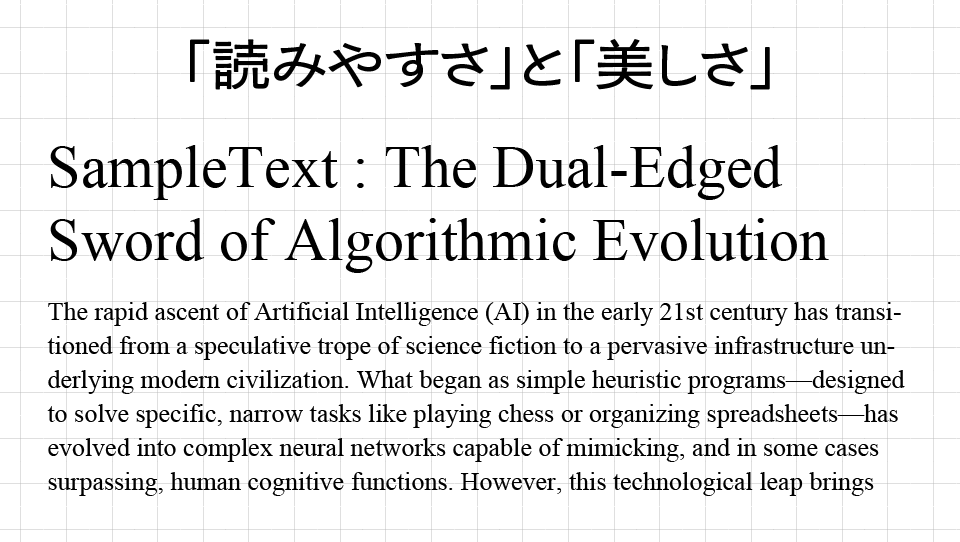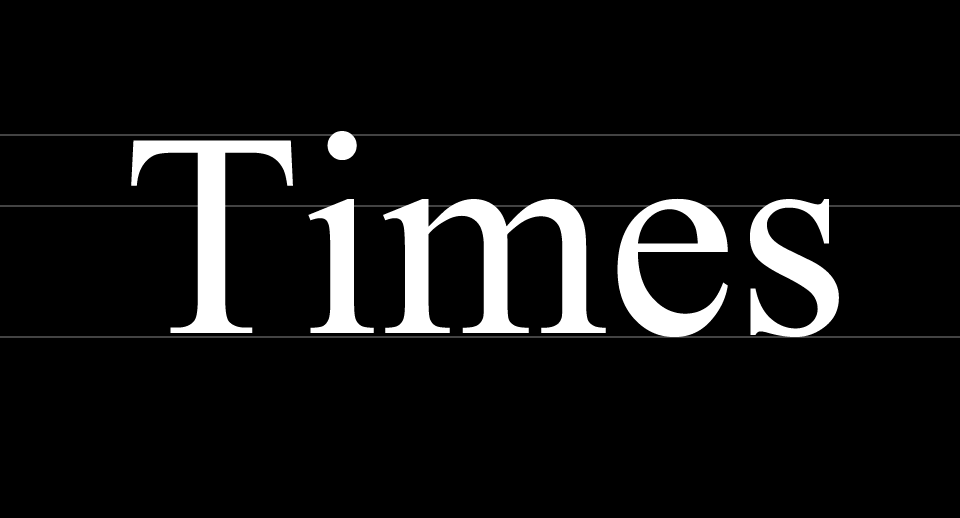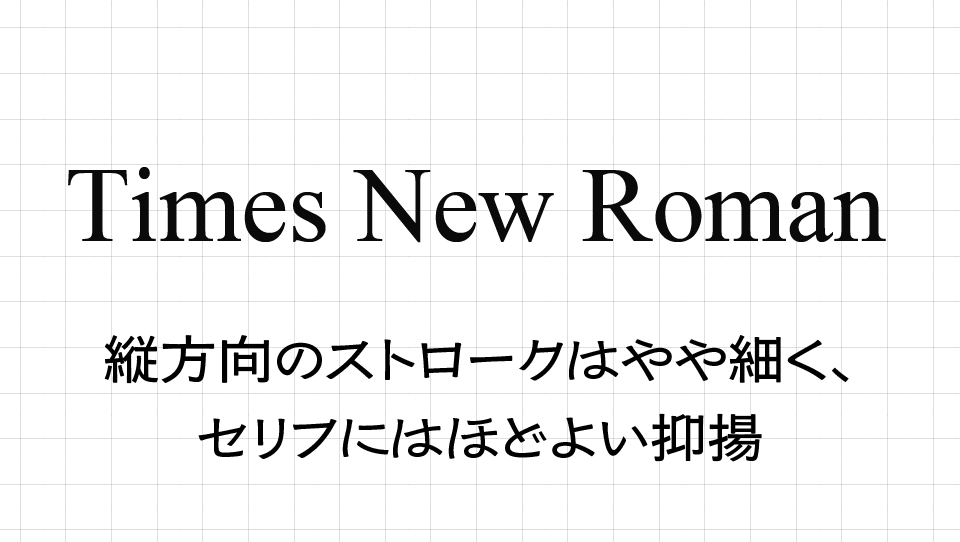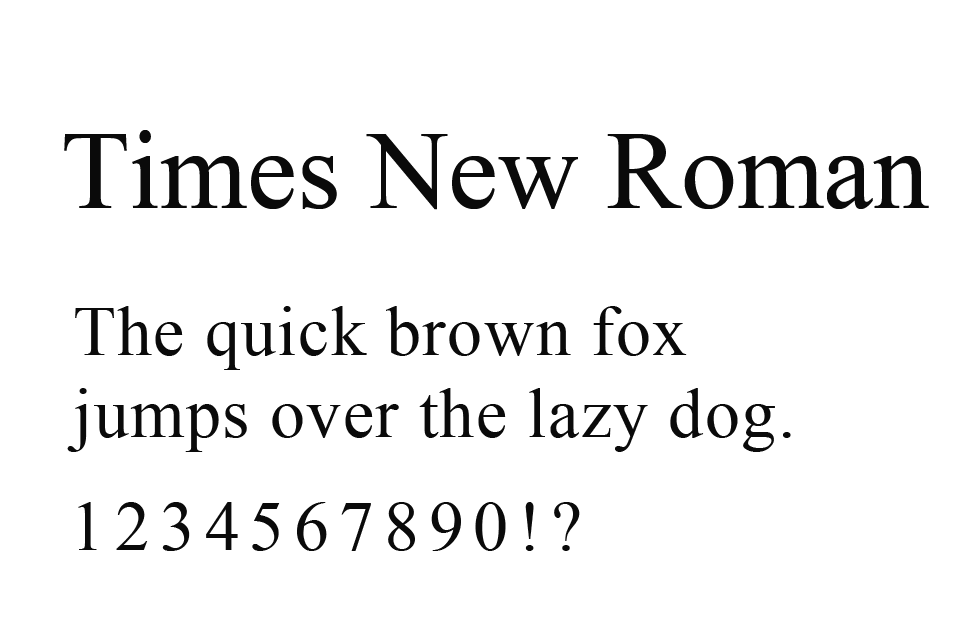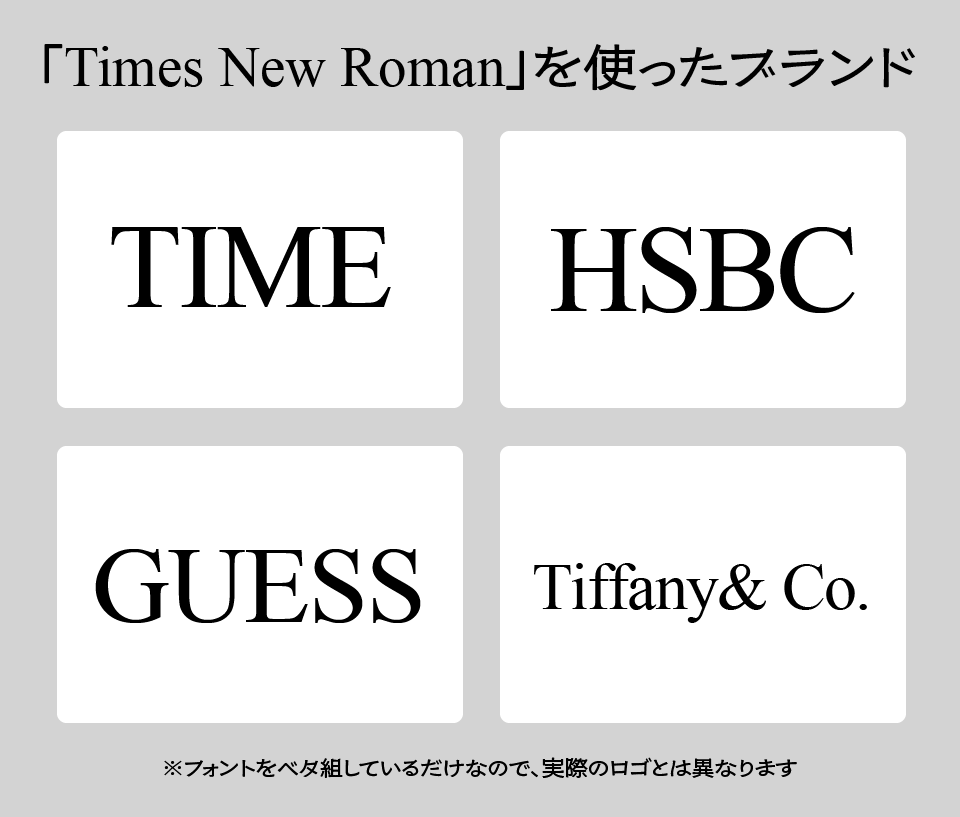
Times New Roman(タイムズ・ニュー・ローマン)フォントの魅力とは?信頼感と可読性を両立するタイポグラフィの定番
シンプルで読みやすく、落ち着いた雰囲気があり、どこか知的な印象を与える。そんな欧文フォントの代表格といえば、Times New Roman(タイムズ・ニュー・ローマン)です。学生のレポートから新聞の紙面、ビジネス文書、学術論文に至るまで、このフォントを一度も見たことがない人はほとんどいないのではないでしょうか。
この記事では、Times New Romanの誕生背景からその設計思想、特徴、代替フォント、実際に使われている事例までを紹介しながら、なぜこのフォントが“定番中の定番”として長年にわたって支持され続けているのかを掘り下げていきます。
Times New Roman(タイムズ・ニュー・ローマン)とは
Times New Romanは、1931年にイギリスの新聞「The Times(ザ・タイムズ)」のために開発されたセリフ体フォントです。設計者は、英国人タイプデザイナーのスタンリー・モリソン(Stanley Morison)と、モノタイプ社のエンジニアであるヴィクター・ラーダー(Victor Lardent)。新聞紙面において「より読みやすく、効率よく情報を伝える」ことを目的にデザインされました。
その後、Times New Romanは印刷媒体にとどまらず、Microsoft Officeに標準搭載されたことで、世界中に普及。パソコンやスマートフォンが身近になった現代においても、もっとも目にすることの多い書体のひとつとなっています。
Times New Romanの歴史と背景
1930年代当時、The Times紙は紙面の刷新を検討しており、モリソンに新しい書体の開発を依頼しました。モリソンは当時の主流だったセリフ体よりもよりコンパクトかつ高い可読性を実現することを目指し、新聞紙面という限られたスペースでも情報がぎっしり詰め込めるようなフォントを設計します。
完成したTimes New Romanは、1932年に紙面上で使用が開始され、その明瞭さと印刷効率の良さから高く評価されました。のちにMonotype社が商用化し、タイプライター、書籍、デジタル文書などへと用途を広げていきます。1992年にはMicrosoft Windowsの標準フォントとしても採用され、一躍「最も一般的なフォント」となりました。
Times New Romanの特徴
Times New Romanの最大の特徴は、高い可読性と情報密度のバランスにあります。文字の縦方向のストロークはやや細く、セリフ(文字端の飾り)にはほどよい抑揚があるため、長文でも読み疲れしにくい設計になっています。曲線と直線の流れが自然で、文字間のリズムも整っているため、視線をスムーズに次の単語へと誘導します。
また、xハイトがやや控えめで、アセンダー(f, l などの上に伸びる部分)やディセンダー(g, y などの下に伸びる部分)がしっかりと取られており、文字それぞれに十分な“呼吸感”があります。一方で、文字幅は比較的狭めに設計されており、限られたスペースでも多くの情報を収められる点が新聞向けに最適化された証でもあります。
類似・代替フォント
Times New Romanは多くの環境に標準搭載されていますが、印象を少し変えたい、あるいはライセンス条件に合わせて別フォントを使いたいときには、以下のような代替フォントが検討されます。
類似・代替フォント
Macユーザー向けのTimesフォントは名前が似ていますが、細部の設計が異なります。
Google FontsのTinosはTimes New Romanを意識したデザインで、Webでも扱いやすい設計になっています。また、Georgiaはややxハイトが高く、Timesよりやわらかく温かみのある印象を与えるため、親しみやすさを出したいときに適しています。
Times New Roman採用している事例
Times New Romanが採用されている分野は非常に広く、特に以下のような場面で「定番の選択肢」として使われています。
Times New Romanを採用している事例
まず、学術論文やレポートでは、多くの大学やジャーナルでTimes New Romanが推奨されています。これは読みやすさと信頼感、整った文字組が評価されているためです。
また、ビジネス文書や履歴書でも、フォーマルかつ中立的な印象を与える書体として多用されています。プレゼン資料や契約書など、文字の可読性が求められるシーンで安定した選択肢として存在しています。
さらに、出版業界では、教科書、小説、新聞記事、広報誌など、紙面レイアウトでの“読みやすさの基準”として今も重宝されています。
Times New Romanを使うときの注意点
Times New Romanは非常に汎用性が高いフォントですが、その「無難さ」が裏目に出るケースもあります。たとえば、デザイン性や個性を重視したいクリエイティブな資料においては、「ありきたり」「堅苦しい」という印象を与える可能性があります。
Times New Romanを使うときの注意点
また、画面上での小さなサイズでは、細部がややつぶれて見えることもあるため、表示サイズや解像度との相性に注意が必要です。紙面とデジタルでは見え方が異なるため、印刷用とWeb用で使い分けるのが理想的です。
Times New Romanは、「静かな信頼」を語るフォント
Times New Romanは、派手な装飾や強い主張はありません。でもそのぶん、長く読まれる文章や、誠実に伝えたい言葉を、淡々と、そして丁寧に支えてくれる存在です。読むことが“作業”ではなく、“向き合う時間”であるように。そんな気持ちをそっと後押ししてくれるフォントだと思います。
文章にとって「書体」とは、声のトーンのようなもの。Times New Romanは、落ち着いていて、理性的で、信頼のおける語り手のようです。もしあなたが、内容そのものの重みや真面目さをしっかり伝えたいとき、このフォントはきっと最良のパートナーになってくれるでしょう。